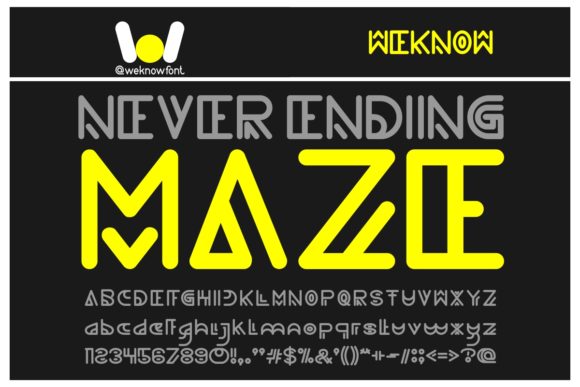
1a Never Ending Maze Font
[1a] Never Ending Maze Font
Never Ending Maze - это причудливый геометрический шрифт, который можно добавить к широкому спектру повседневных дизайнов, так как он выделит каждый из них.